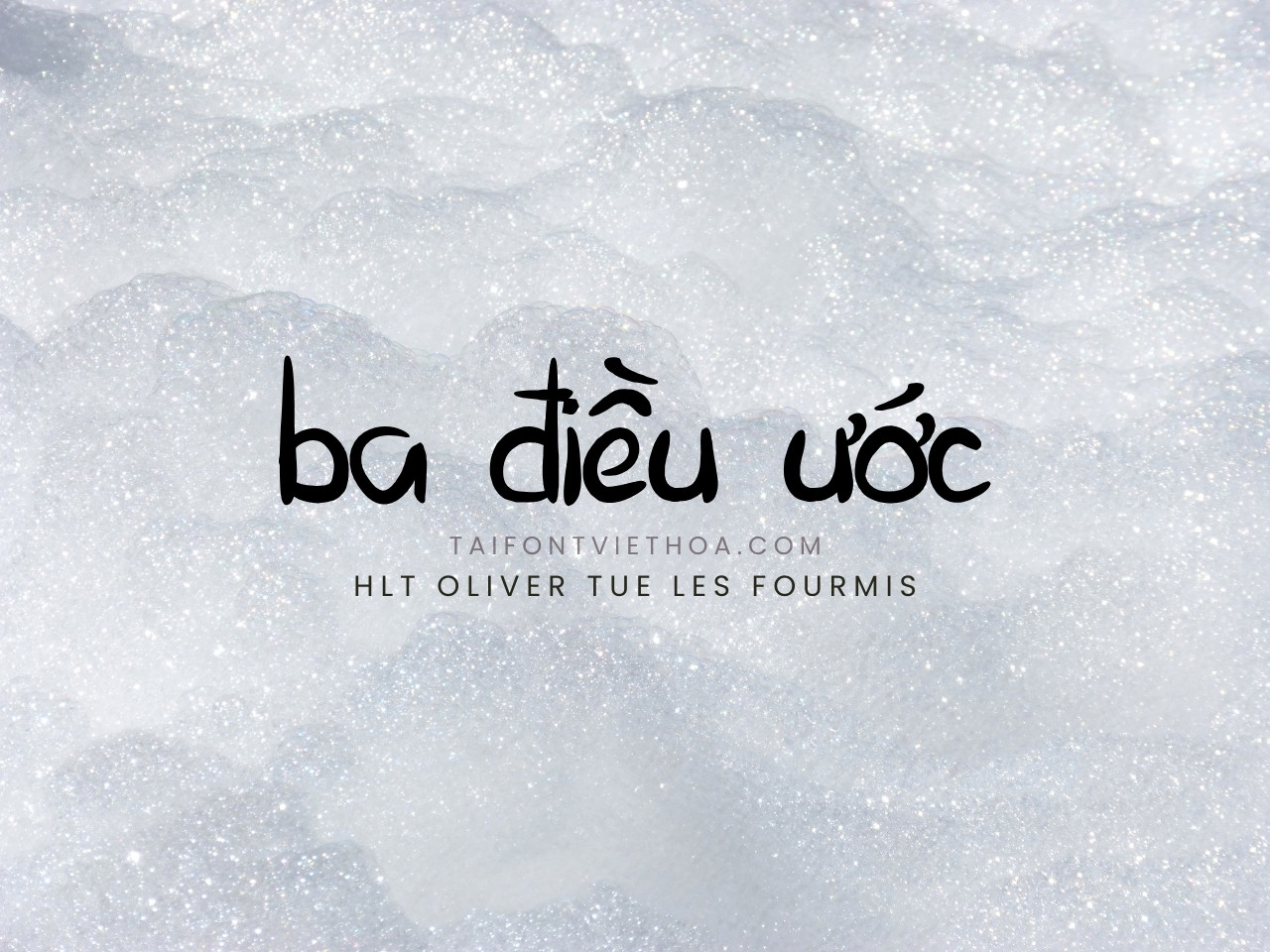
Giới thiệu về font Oliver Tue Les Fourmis – Nét đẹp cổ tích giữa thời hiện đại
Oliver Tue Les Fourmis là một font chữ viết tay (handwritten) mang phong cách độc đáo và tinh nghịch, được thiết kế bởi Olivier Gourvat – nhà thiết kế đến từ Pháp, sáng lập Typofonderie. Font mang tên kỳ lạ “Oliver giết kiến” này không chỉ tạo ấn tượng bởi cách đặt tên mà còn bởi cách thể hiện nét chữ mềm mại, bay bổng và pha một chút hóm hỉnh. Font gốc được phát hành trên nền tảng thương mại quốc tế và hỗ trợ hơn 50 ngôn ngữ thuộc hệ Latinh, đáp ứng tốt cho các thiết kế đa văn hóa.
Phiên bản Việt hóa do HLT Fonts thực hiện đã bổ sung đầy đủ dấu và ký tự đặc trưng tiếng Việt, đảm bảo tính thẩm mỹ và tương thích cao với nội dung tiếng Việt. Không chỉ chuyển ngữ, nhóm Việt hóa còn tinh chỉnh chi tiết để từng đường nét hài hòa hơn với bảng chữ cái có dấu. Font này đã được taifontviethoa.com chọn lọc, sưu tầm và chia sẻ nhằm phục vụ cộng đồng thiết kế Việt trong các dự án cần sự trẻ trung, sáng tạo và mang dấu ấn cá nhân rõ nét.
Đặc điểm thiết kế và khả năng ứng dụng của HLT Oliver Tue Les Fourmis
Font Oliver Tue Les Fourmis sở hữu kiểu chữ viết tay ngẫu hứng, có phần thô ráp nhưng rất biểu cảm, tạo cảm giác gần gũi như chữ viết tay thực tế. Độ cao thấp không đồng đều, nét chữ dao động nhẹ khiến mỗi dòng văn bản như một phần của cuốn nhật ký cá nhân. Dù mang vẻ ngây thơ, font vẫn giữ được độ cân đối cần thiết, nhờ đó vẫn dễ đọc trong nhiều ngữ cảnh sử dụng.
Font này đặc biệt phù hợp với các thiết kế dành cho trẻ em, bìa truyện tranh, poster hoạt hình, thiết kế sách ảnh, namecard nghệ thuật hoặc thương hiệu cá nhân mang tính sáng tạo. Ngoài ra, font cũng có thể ứng dụng trong các chiến dịch quảng bá sản phẩm thủ công, đồ chơi, quà tặng, hoặc các hoạt động giáo dục tương tác.